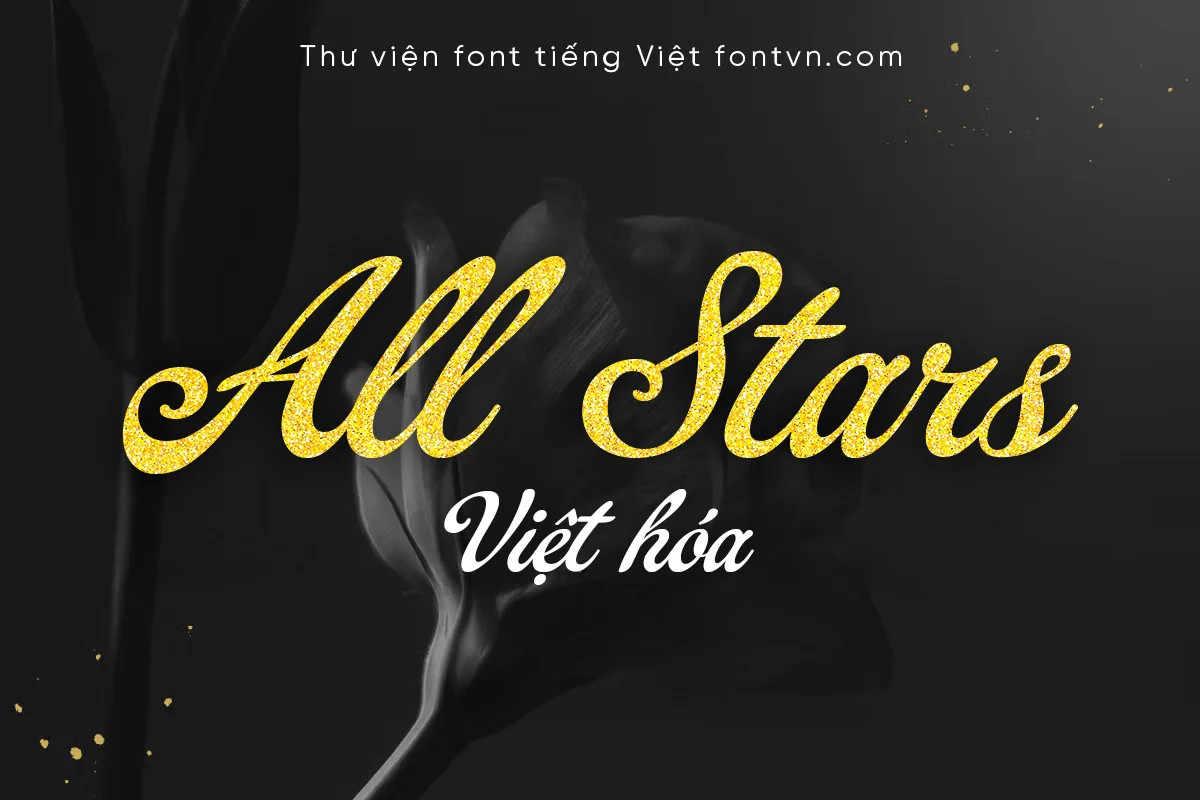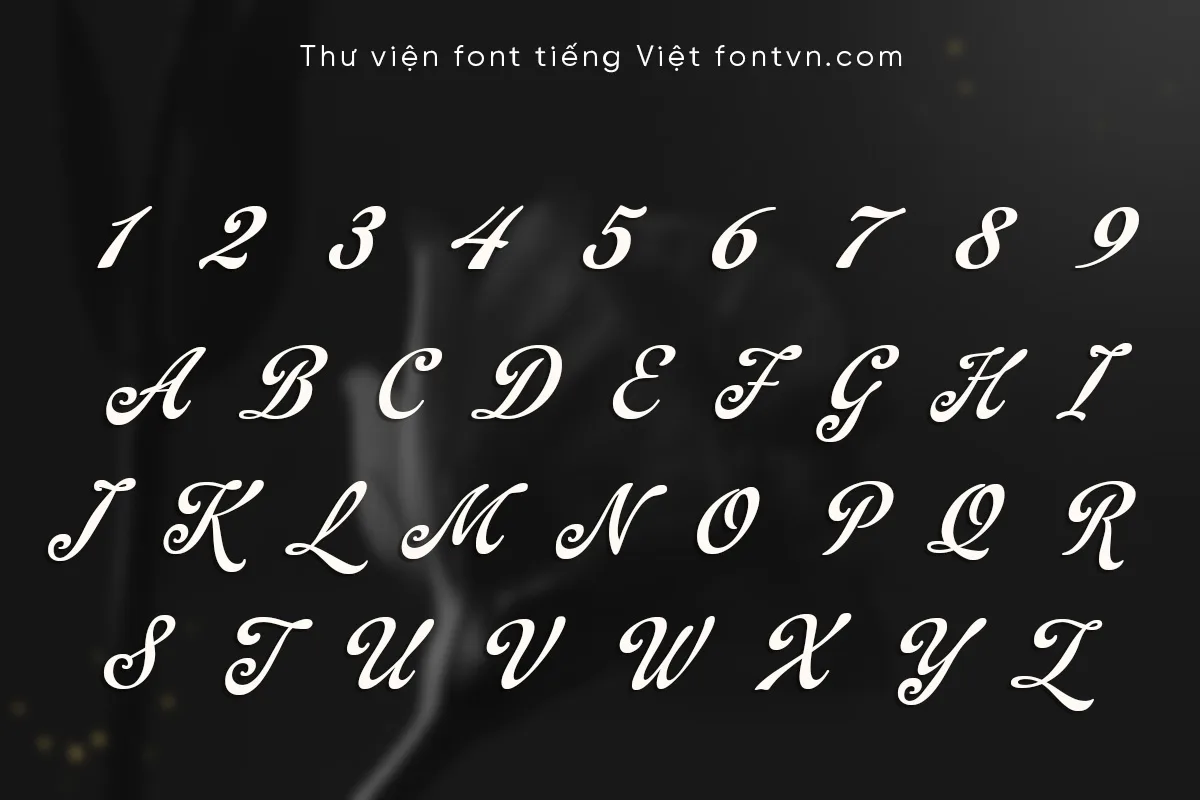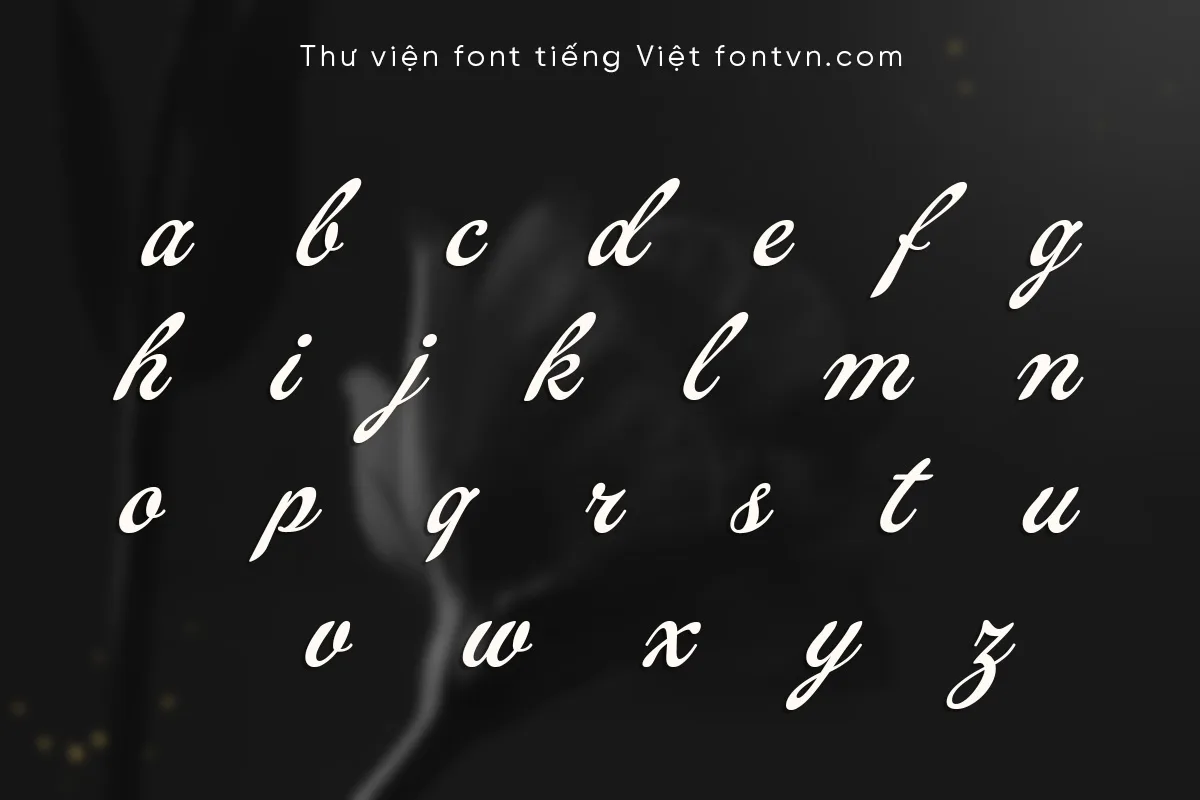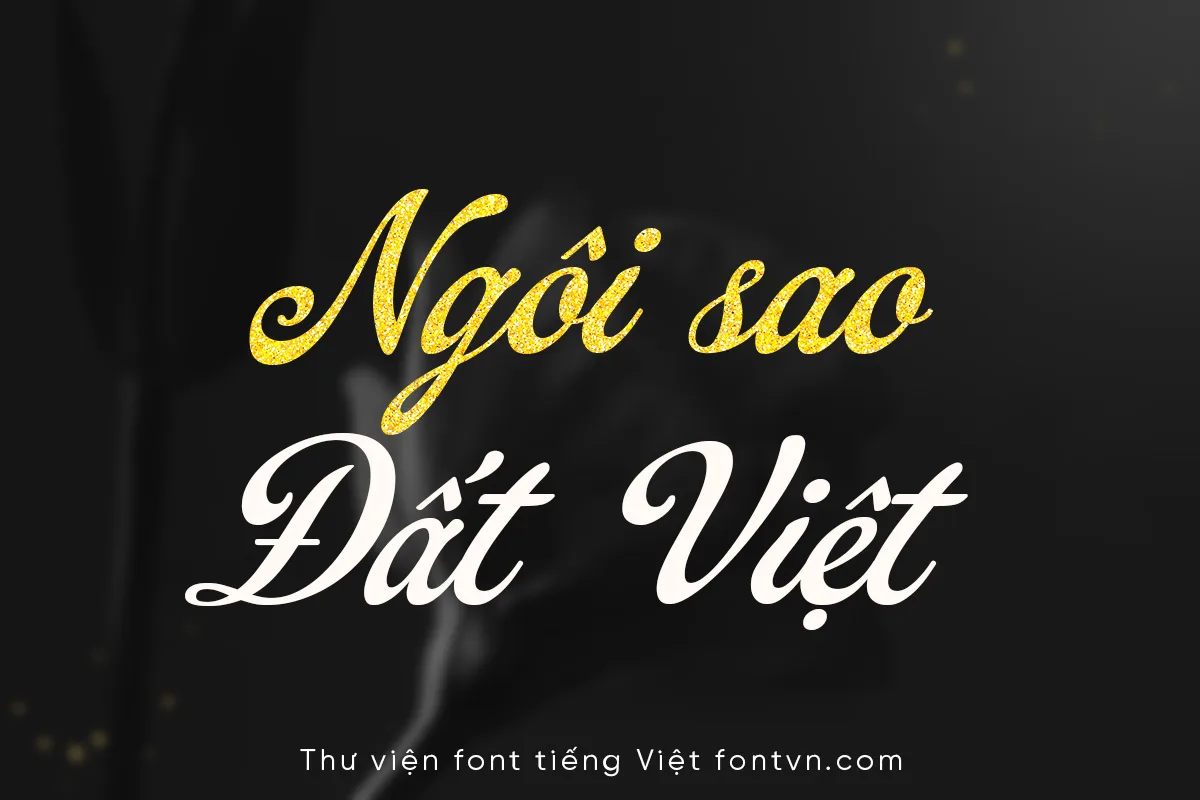
DVN All Stars – Font Script Thanh Lịch & Tối Ưu Hiển Thị
DVN All Stars là font chữ script có cấu trúc chắc chắn với độ tương phản nét thanh – nét đậm rõ ràng. Các ký tự in hoa được thiết kế kèm nét vuốt (swash) vừa đủ để tạo điểm nhấn, trong khi hệ thống chữ thường có x-height đồng đều và nối liền mạch, giúp tối ưu khả năng đọc. Với tính ứng dụng cao, font chữ này phù hợp để thiết kế logo, tiêu đề chính, bao bì hoặc thiệp mời, mang lại sự chuyên nghiệp, trực quan và giải quyết tốt bài toán tối ưu chi phí cho các dự án thiết kế.